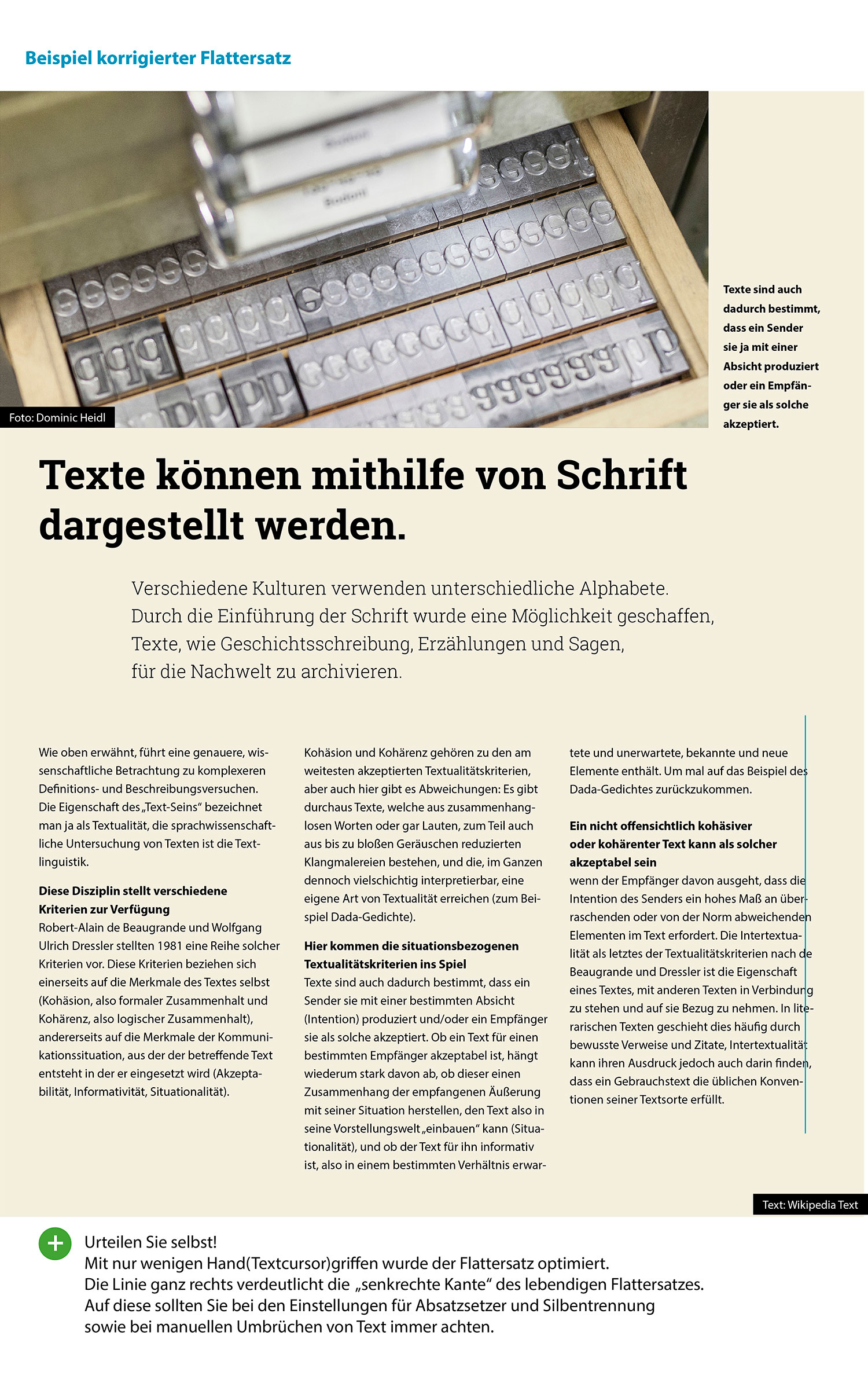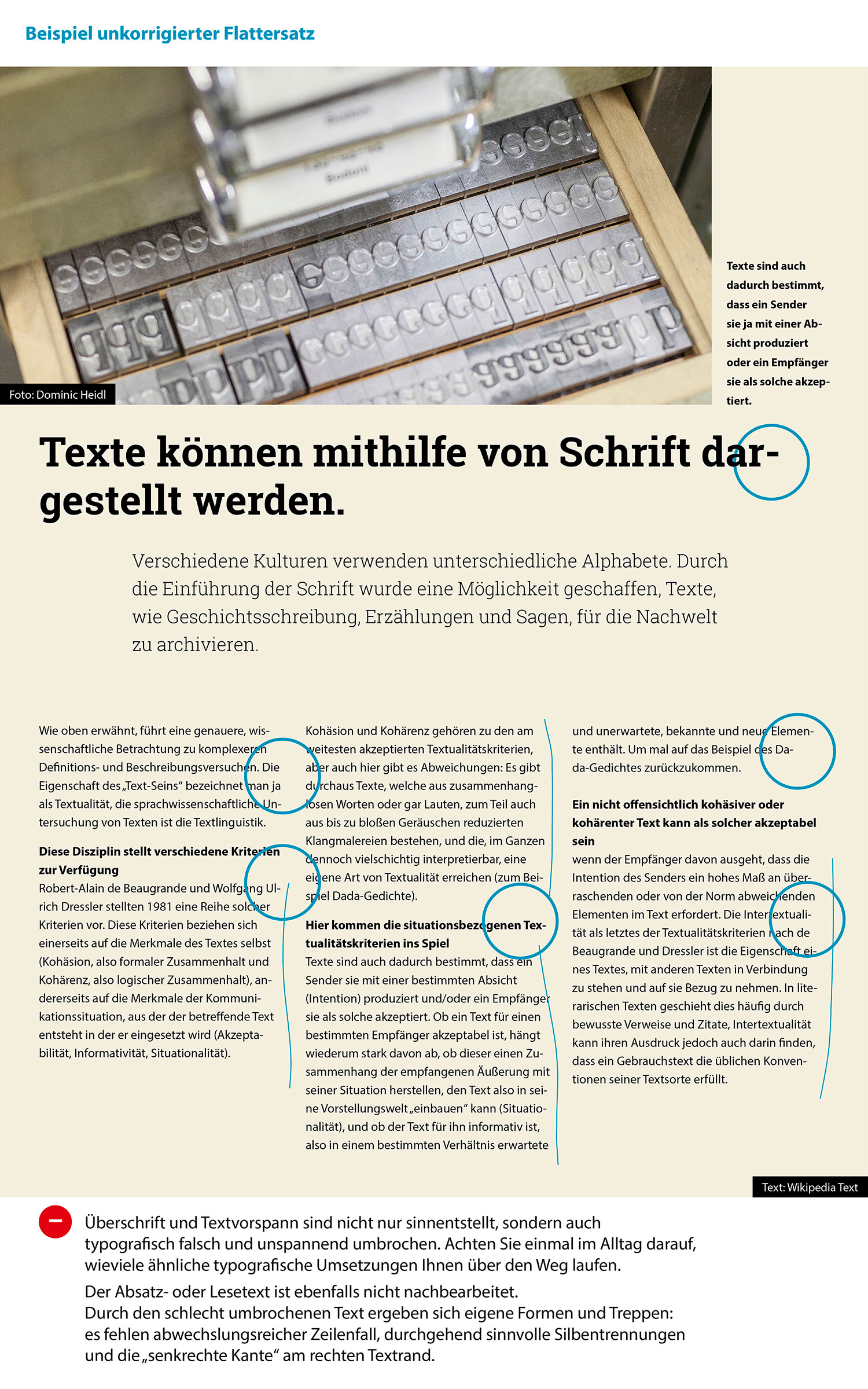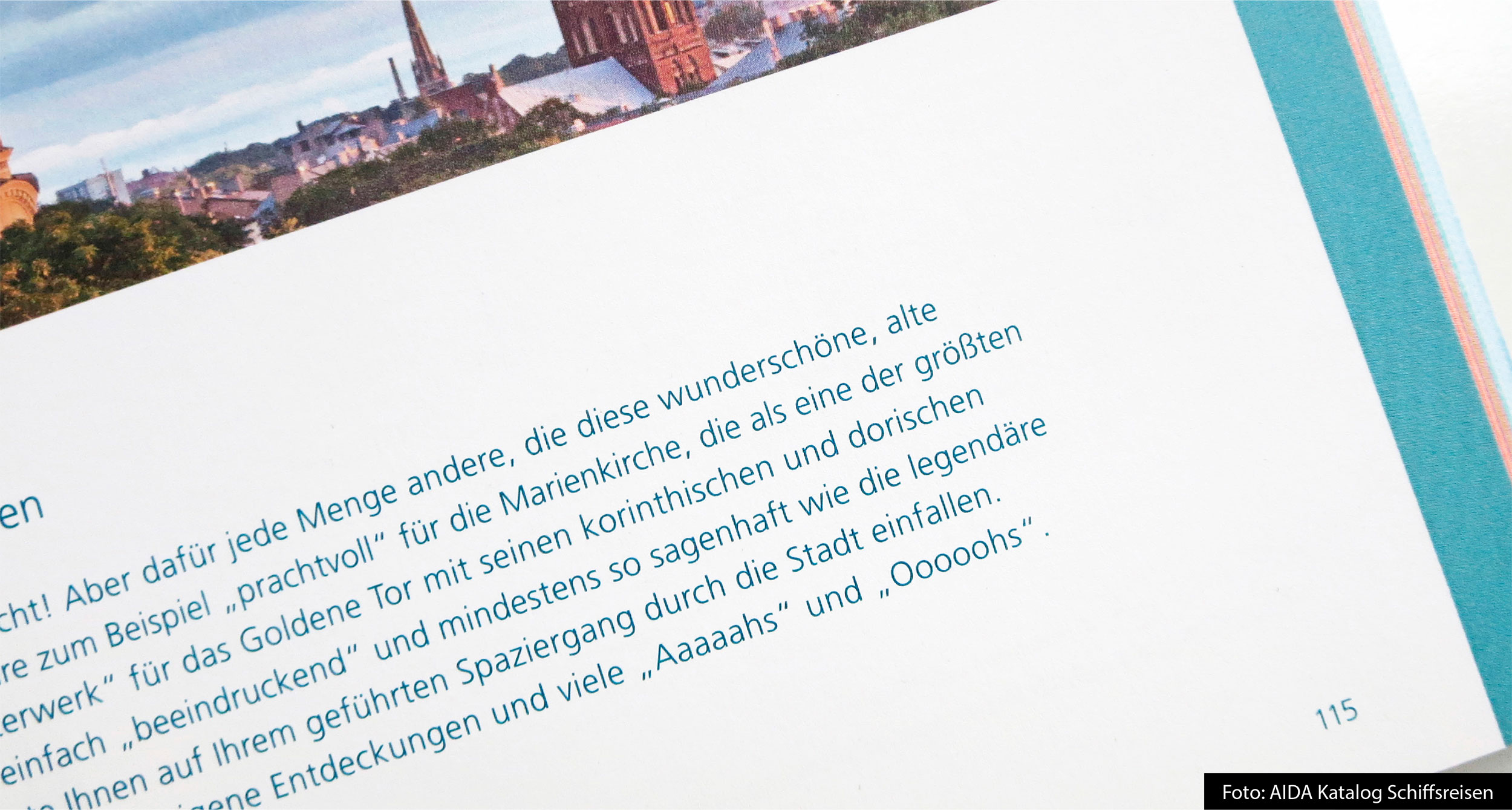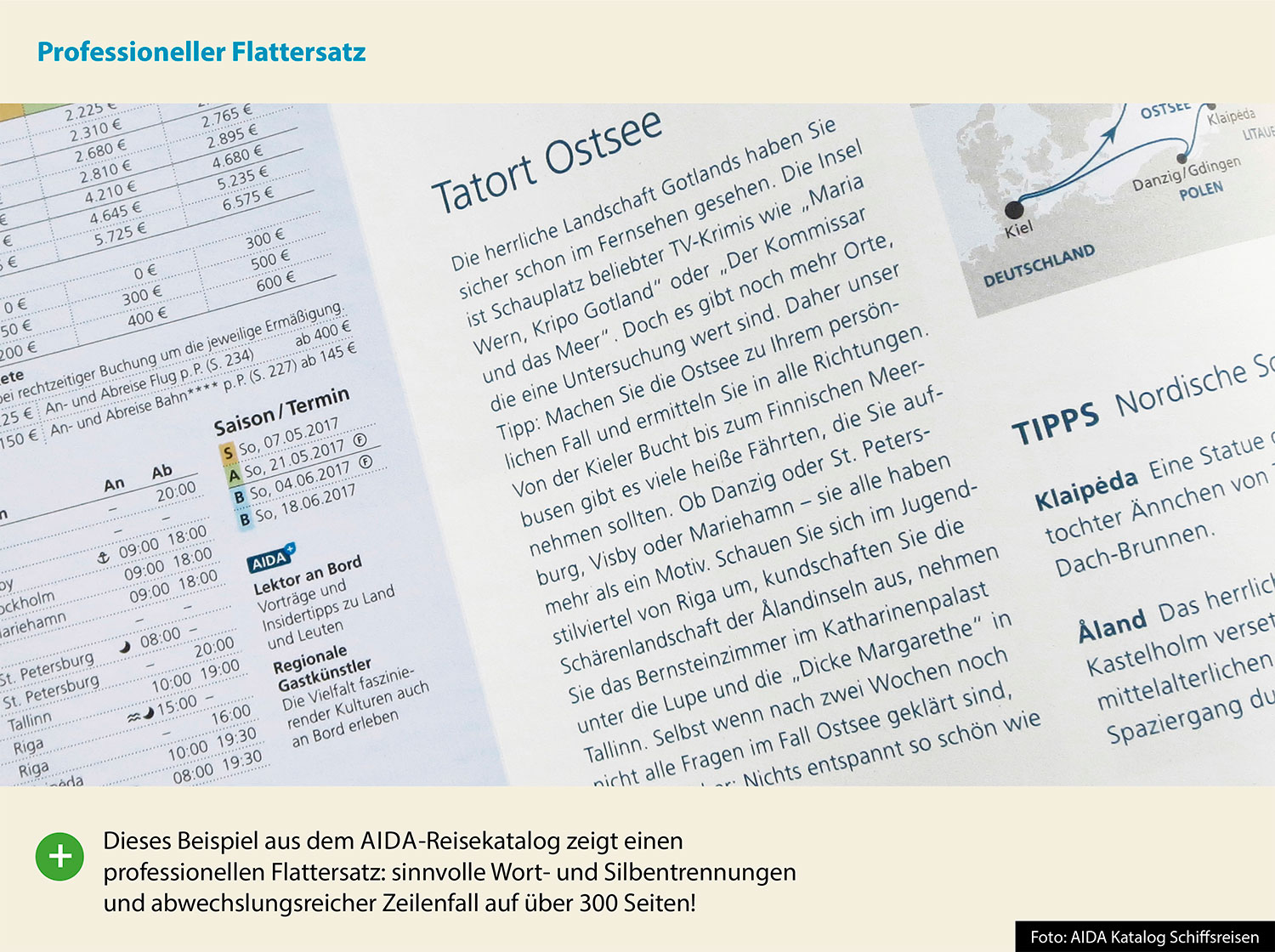
Typografie: Flattersatz soll flattern …
Die wohl meistverwendete Satzart
Was eigentlich selbstverständlich sein sollte, ist leider selten anzutreffen, nämlich Flattersatz, der flattert.
Der Flattersatz ist die am häufigsten angewendete Satzart, denn sie wirkt im Gegensatz zum Blocksatz lebendig, leicht und weniger streng. Deshalb wird der Flattersatz bevorzugt für Headline, Textvorspann oder Kapitelüberschriften sowie für kürzere Lesetexte im Akzidenzsatz oder bei Werbetext verwendet.
Im Flattersatz wenden wir die Satzformen links- oder rechtsbündig (libü oder rebü) an, wobei wir der besseren Lesbarkeit wegen den linksbündigen Flattersatz bevorzugen. Rechtsbündiger Flattersatz verwenden wir als typografische Auszeichnungsform bei kürzeren Texten, z. B. Bei Marginaltext, Textvorspann oder Bildunterschriften, wenn die Texte vertikal an Bildern, Linien oder anderen grafischen Elementen ausgerichtet sind.
Flattersatz soll flattern
Die Annahme, dass ein schöner Flattersatz sich wie von selbst durch Voreinstellungen im Programm realisieren lässt, ist falsch. Genau wie beim Blocksatz benötigt auch der Flattersatz ein kritisches Auge und oft auch eine manuelle Nachbearbeitung. Die häufigsten Gründe dafür:
• der Zeilenfall hat wenig Rhythmus, weil er aus ähnlich langen Zeilen besteht und somit eher wie Blocksatz aussieht,
• der Zeilenfall bildet extreme Treppen oder Formen,
• es entstehen sinnentstellende Silbentrennungen.
Auf die richtige Trennung kommt es an
Neben einem guten und abwechslungsreichen Zeilenfall haben sinnvolle Silbentrennungen Priorität. Nach dem Einfließen von Text sollte daher geprüft werden, ob die ausgeführte Silbentrennung korrekt und sinnvoll ist. Nicht nur bei einem prominenten Vorspanntext sollte dann manuell nachgearbeitet werden.
Im professionellen Flattersatz sind sinnvolle Trennungen und ein abwechslungsreicher Zeilenfall nach dem Prinzip »kurze – lange – mittellange Textzeile« ausgeführt und hat dabei dennoch eine gleichmäßig verlaufende rechte Satzkante, wie das untere Beispiel aus einem Reisekatalog zeigt.
Manuelle Trennungen und Voreinstellung Silbentrennung
Möchten Sie den Flattersatz manuell nachbearbeiten, so empfehle ich Ihnen, unter Schrift/Absatz den Adobe Ein-Zeilen-Setzer auszuwählen. Dieser bewirkt, daß keine Neuumbrüche im Satz entstehen, wenn Sie ein Wort umbrechen. Silbentrennungen sollten natürlich nur mit dem „bedingten Trennstrich“ durchgeführt werden, damit bei der Rückführung einer Trennung kein Divis stehen bleibt.
Mein Praxis-Tipp für den Flattersatz:
• Wenden Sie Flattersatz eher für kürzere Texte als für lange Magazintexte an, da diese Satzart leichter und lebendiger wirkt.
• Achten Sie im Idealfall auf einen abwechslungsreichen Zeilenfall nach dem Prinzip: Kurz – Lang – Mittellang – Lang – Kurz – Mittellang …, usw.
• Prominente Texte wie Vorspanntexte benötigen nach diesem Prinzip besondere Aufmerksamkeit und müssen in der Regel manuell nachgearbeitet werden.
• Worttrennungen im Flattersatz sind durchaus erlaubt. Achten Sie dabei aber auf sinnvolle Silbentrennungen mit dem „bedingten Trennstrich“.
• Achten Sie darauf, dass der Umbruch bei größeren Textzeilen möglichst nach einem Satzzeichen (Gedankenstrich, Komma oder Punkt) erfolgt.
• Es gilt die Regel: sinnvolle Worttrennungen erfolgen vor abwechslungsreichem Zeilenfall.